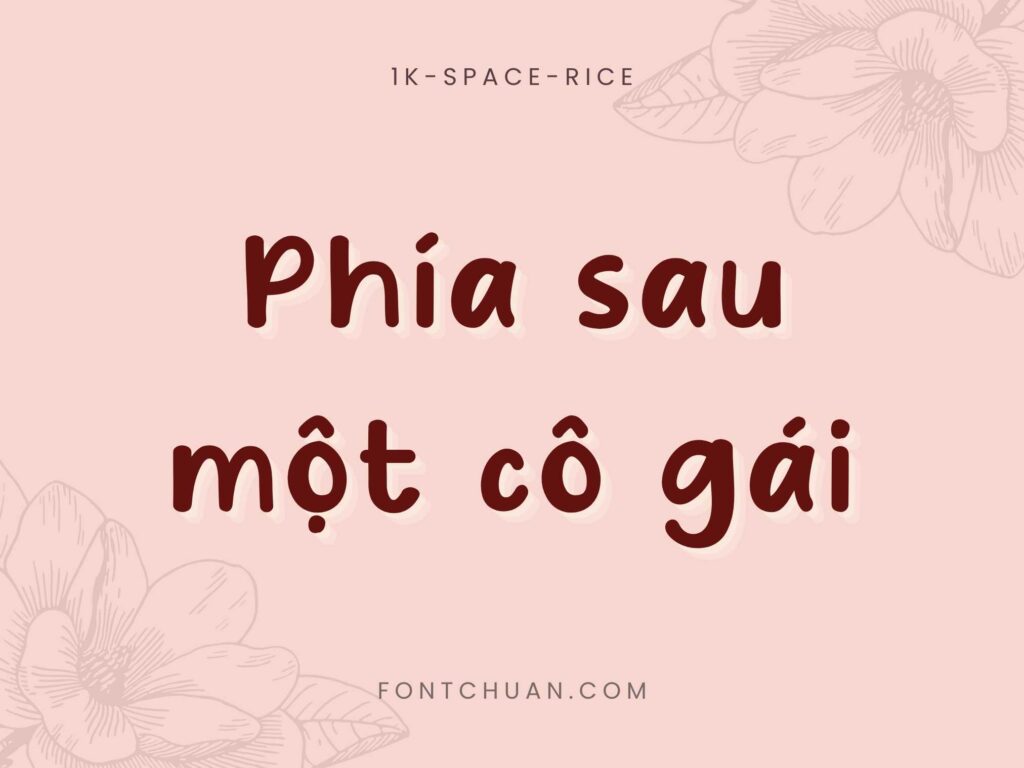
Font 1K-Spacerice Việt Hóa
1K-Space-Rice là phiên bản Việt hóa của phông chữ Space Rice, được thiết kế bởi MJType. Đây là một phông chữ viết tay với phong cách hiện đại, mang lại cảm giác tự nhiên và thân thiện cho các thiết kế. Phiên bản đầu tiên được phát hành vào năm 2024. Font này đã được FontTiengViet Việt hóa, hỗ trợ đầy đủ các ký tự tiếng Việt, giúp người dùng dễ dàng áp dụng trong các dự án thiết kế đa dạng. Ngoài tiếng Việt, font còn hỗ trợ nhiều ngôn ngữ khác, bao gồm tiếng Anh, Pháp, Tây Ban Nha, Đức và Ý. Phông chữ này được thành viên Font Chuẩn sưu tầm và đăng tải nhằm phục vụ nhu cầu sáng tạo phong phú.
Với phong cách viết tay hiện đại và thân thiện, 1K-Space-Rice phù hợp cho các ứng dụng như thiệp mời, tiêu đề, logo và các ấn phẩm in ấn cần sự cá nhân hóa. Các ký tự có độ cao x trung bình, mang lại sự tinh tế và mềm mại cho văn bản. Font cũng bao gồm các ligatures, giúp tăng tính liên kết giữa các chữ cái, tạo nên sự mượt mà trong thiết kế. Trong lĩnh vực sự kiện, phông chữ này có thể được sử dụng trong các dịp như thiệp cưới, lễ hội và sinh nhật. Ngoài ra, 1K-Space-Rice cũng thích hợp cho các ngành nghề như quảng cáo, giáo dục và công nghệ.